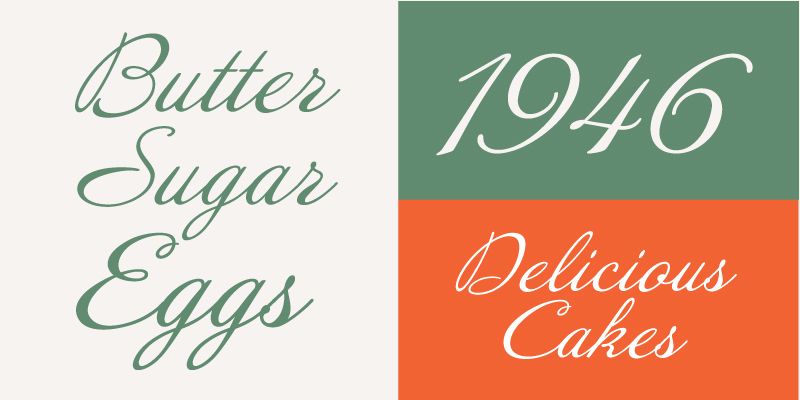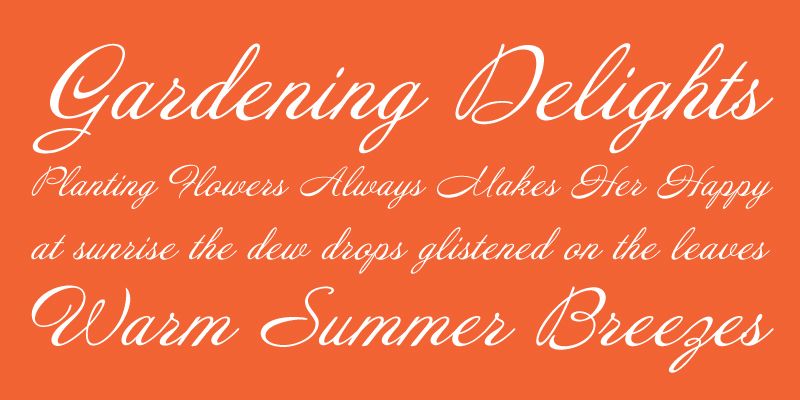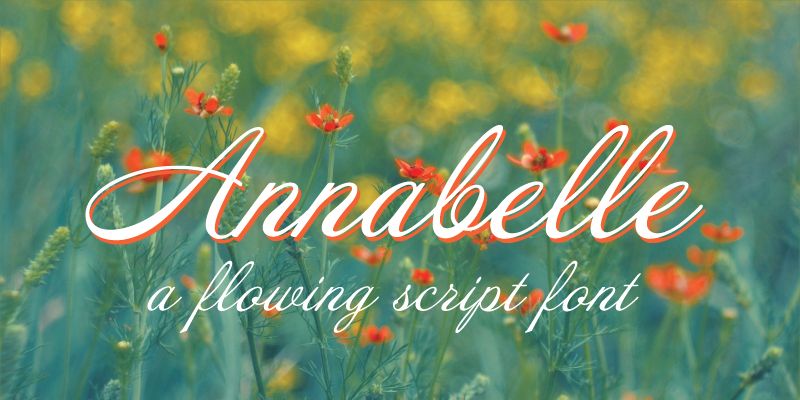
Annabelle é uma bela fonte de escrita original da Jukebox que leva o nome da mãe do designer. Fluida e elegante, Annabelle é perfeita para convites de casamento, capas de livros e muito mais.